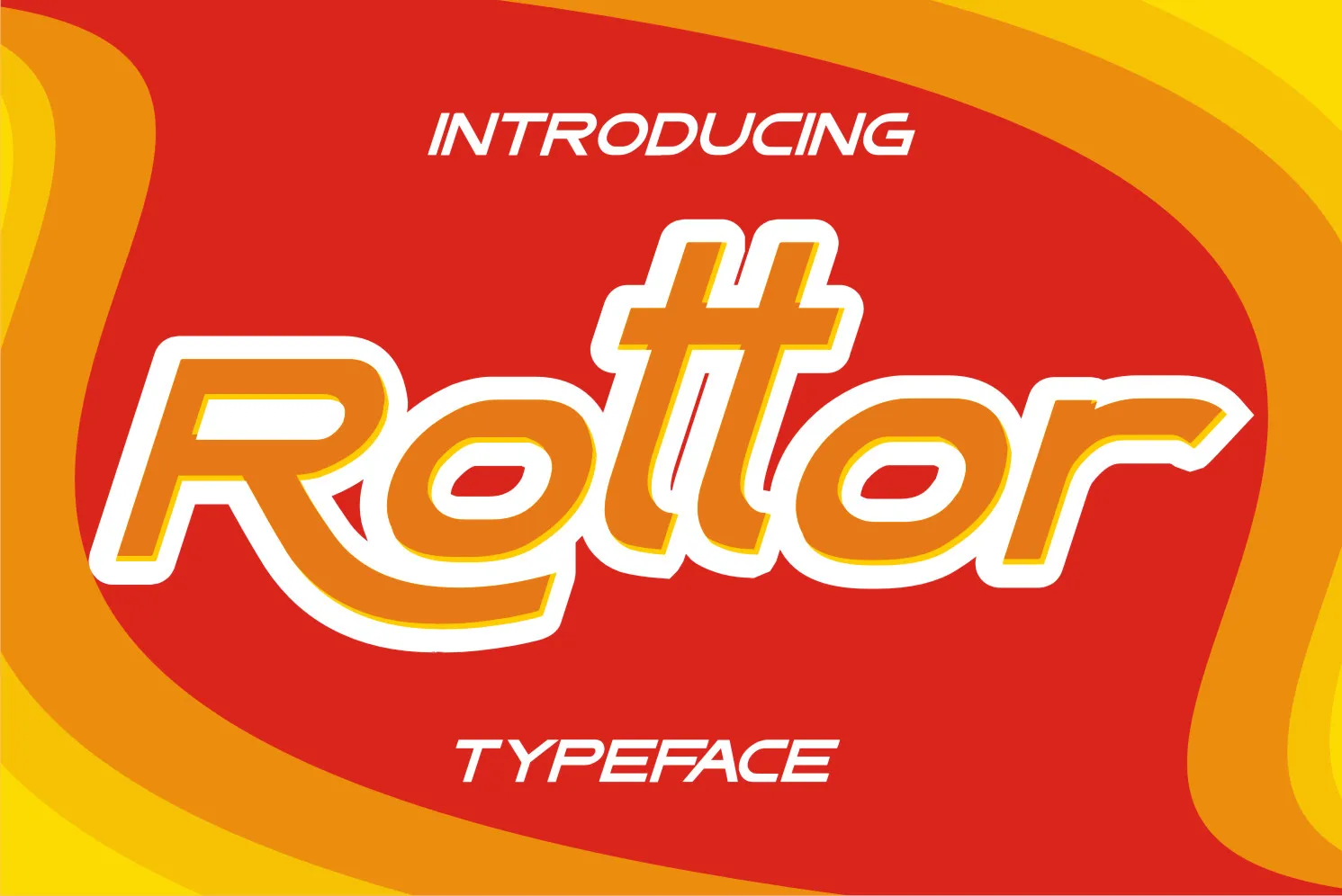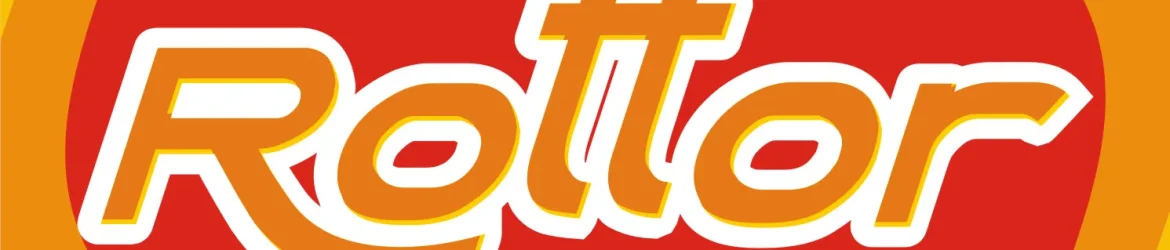
Esta é uma fonte de exibição moderna e cool. A Rottor Font está projetada para se adequar a designs variados, como camisetas personalizadas, roupas esportivas, logotipos, anúncios e muitos outros. É uma escolha perfeita para criar um visual atemporal que combina modernidade com criatividade em qualquer tipo de projeto gráfico. Seja ela a peça principal ou apenas um elemento de destaque, a Rottor Font irá adicionar um toque único ao seu design. Se você está procurando por uma fonte que combine elegância e irreverência, essa pode ser sua escolha perfeita para qualquer aplicação. Não importa se você é um designer gráfico ou uma marca que busca criar um branding impecável, a Rottor Font pode ajudar a transformar seus projetos em algo realmente especial.